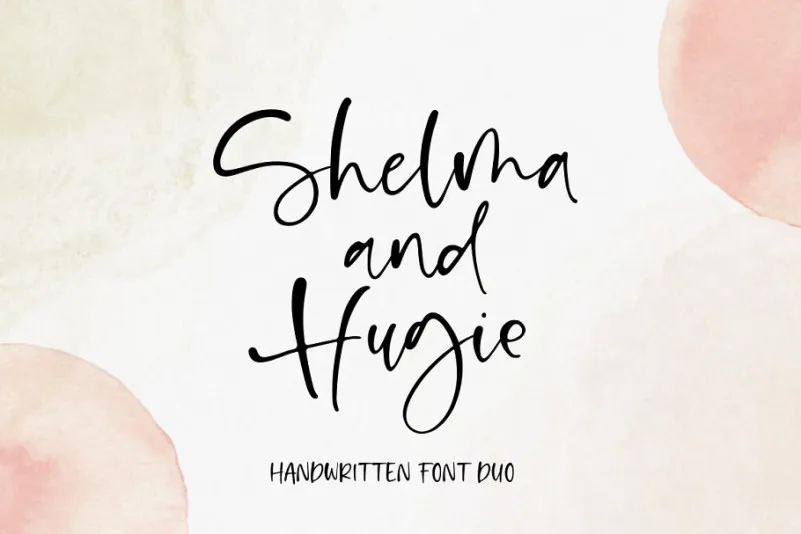
Bem-vindo aos detalhes essenciais sobre a ‘Shelma & Hugie Font Duo’ na categoria de fontes de script. Esta moderna e elegante combinação de escrita manuscrita é perfeitamente projetada para potencialmente aprimorar o seu design, tornando-o ainda mais atrativo e original. Desenvolvida pelo designer zziplex, esta fonte foi feita sobretudo para atender as necessidades do mundo das criações visuais modernas. Os seus riscos manuscritos naturais tornam a ‘Shelma & Hugie Font Duo’ perfeita tanto para design de logotipo e cartões de convite, como para desenhos de estação ou embalagens de produtos. Esta fonte também se destaca em postagem nas redes sociais, anúncios, embalagens de produtos, etiquetas, fotografia e até mesmo marca d’água para eventos especiais ou qualquer outro tipo de projeto visual.